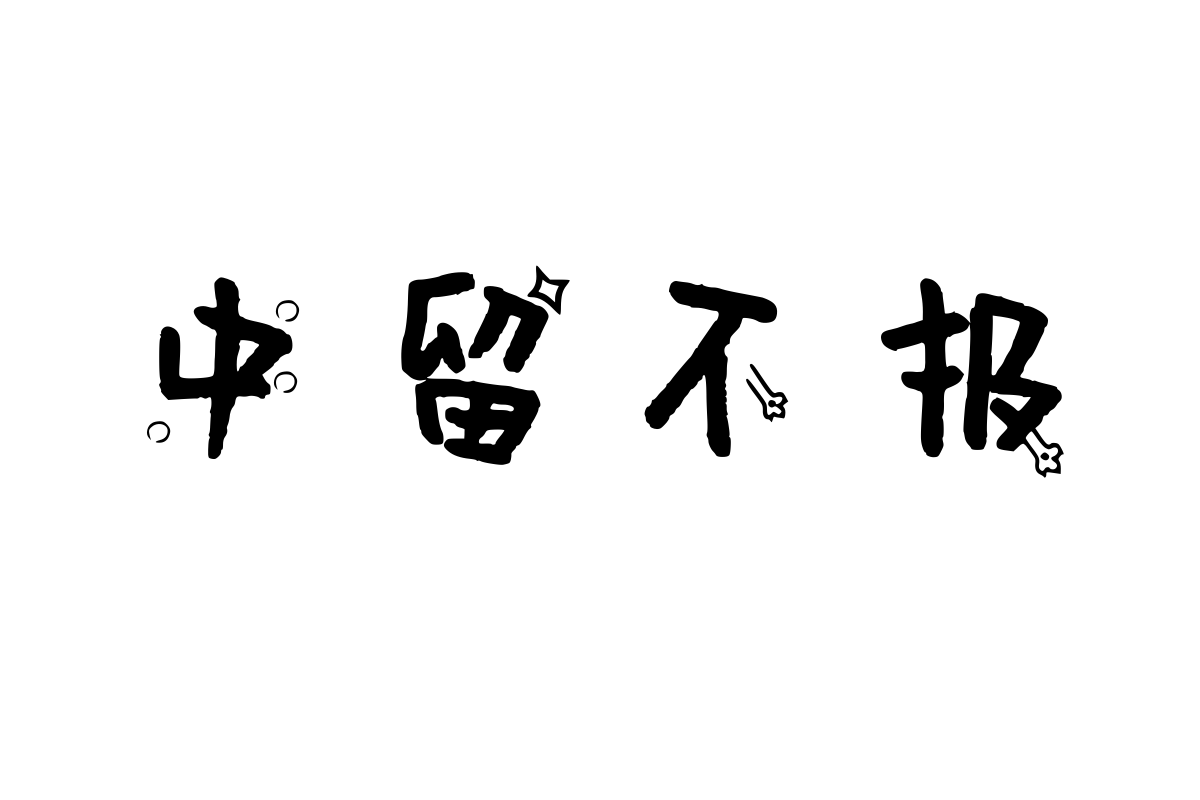
兰米猫爪体是一种中文字体,具有独特的设计风格和特点。这种字体的特点是笔画粗细变化明显,线条流畅自然,给人一种轻盈、灵动的感觉。同时,兰米猫爪体的字形结构紧凑,笔画之间相互支撑,呈现出一种立体感。
兰米猫爪体的笔画粗细变化丰富,既有粗犷的线条,又有细腻的笔触,使得整体视觉效果更加丰富多样。此外,兰米猫爪体的字形结构紧凑,笔画之间相互支撑,使得整个字体看起来更加和谐统一。
总的来说,兰米猫爪体是一种具有独特风格和特点的中文字体,适合用于需要强调个性和创意的设计场合。